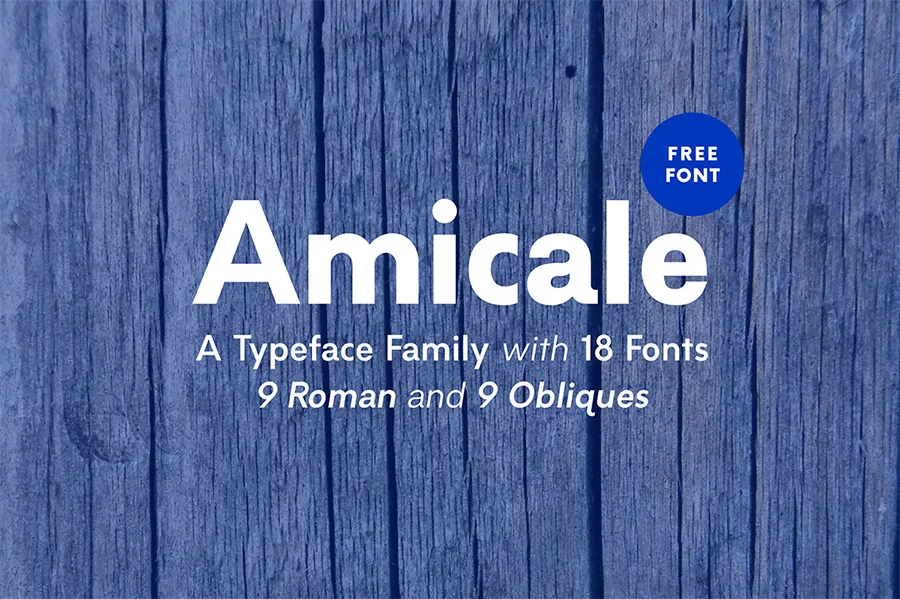
Amicale Typeface – Download Grátis
A Amicale Typeface é uma tipografia sans serif moderna e profissional que destaca-se por sua simplicidade limpa e elegante. Inspirada no design minimalista, esta família de caracteres se integra perfeitamente a qualquer projeto gráfico, seja para criar logotipos claramente definidos ou incorporar em editoriais jornalísticas. O peso regular do Amicale está disponível gratuitamente para download, uma bênção para quem busca estilizar materiais com um visual inovador e contemporâneo. Uma agradecida homenagem é feita ao Alfredo Marco Pr 讀取更多关于全家族版本 的详细信息,以获得更大程度的享受和创意发挥。 Aproveite esta fonte sem custos para personalizar seus projetos de design de maneira única e sofisticada.